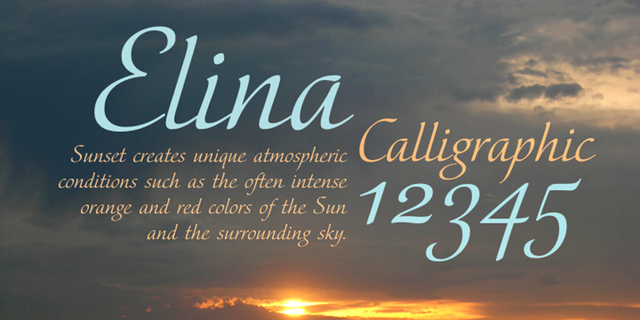
Шрифт Elina (Элина) продолжает серию изящных каллиграфических шрифтов Натальи Васильевой, имитирующих отчасти письмо широким пером. Гарнитура состоит из двух начертаний — обычного и декоративного. В декоративном начертании символы украшены тонкими штрихами, повторяющими фрагменты контура и придающими рисунку нарядность. Шрифты предназначены для акциденции, поздравительных и рекламных текстов. Выпущен компанией ПараТайп в 2010 году